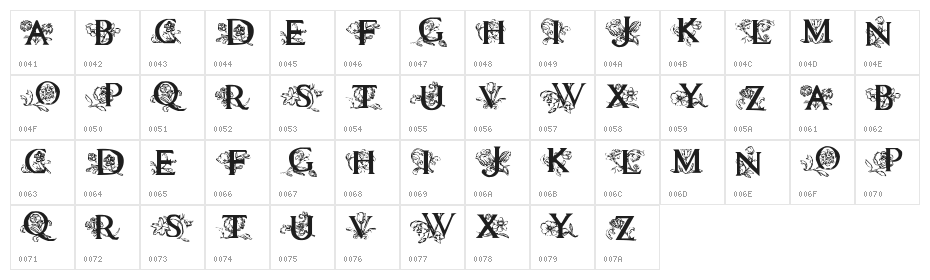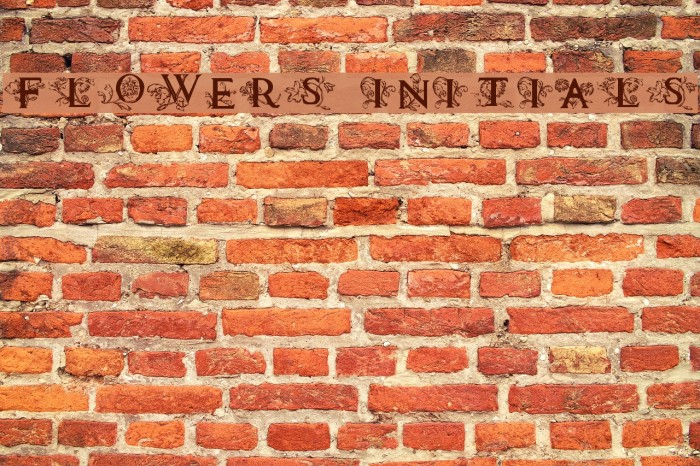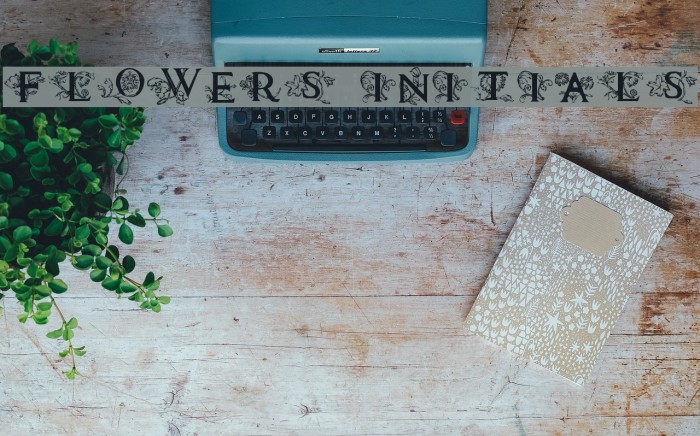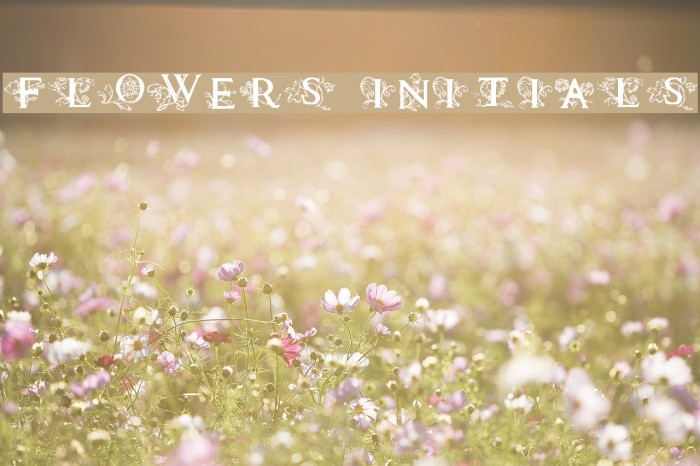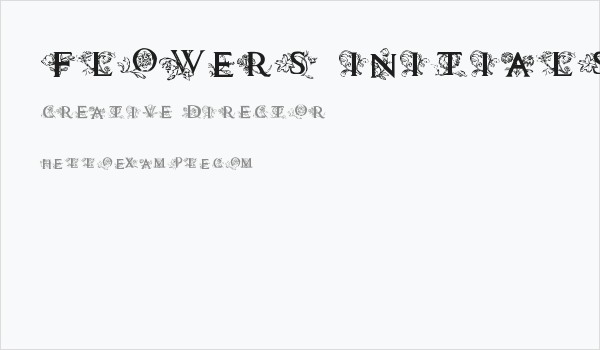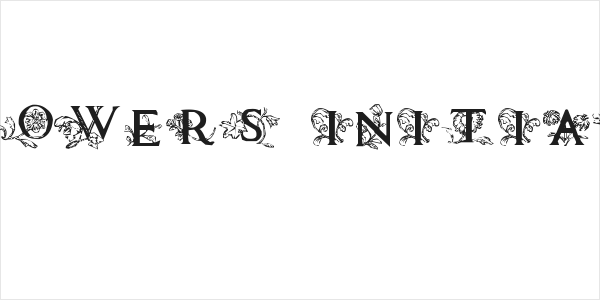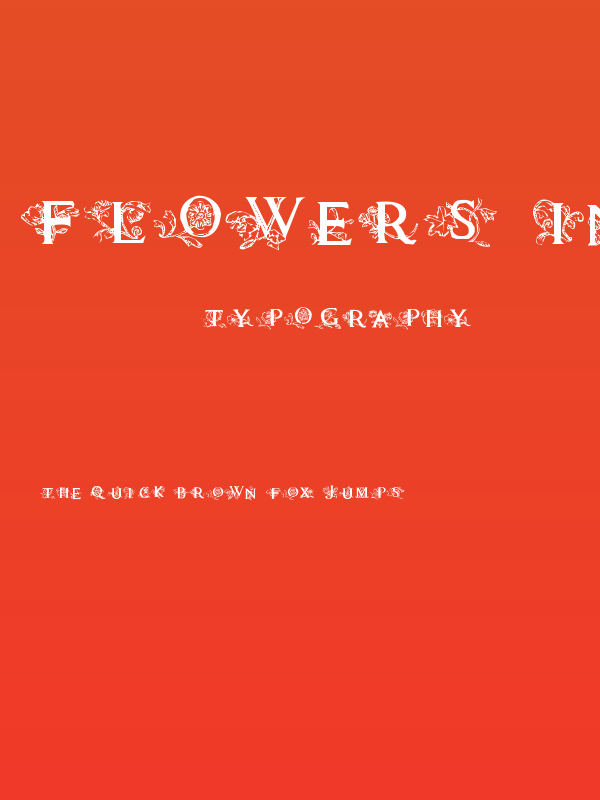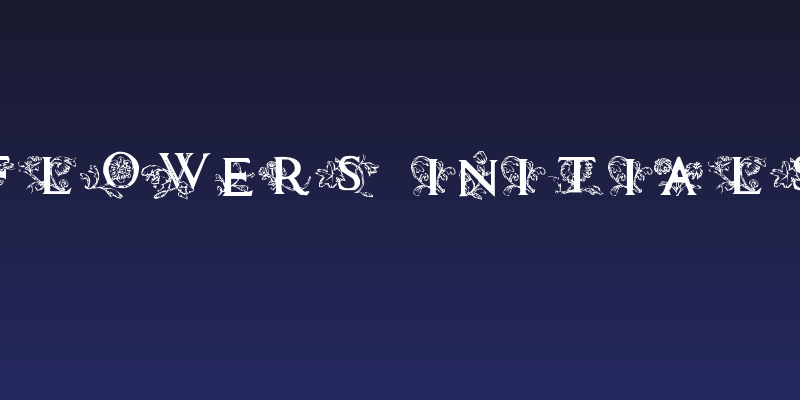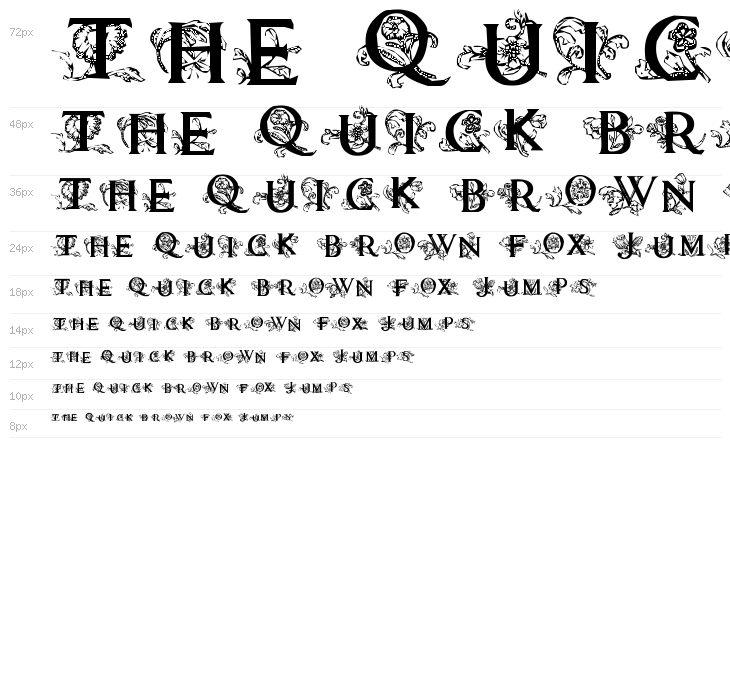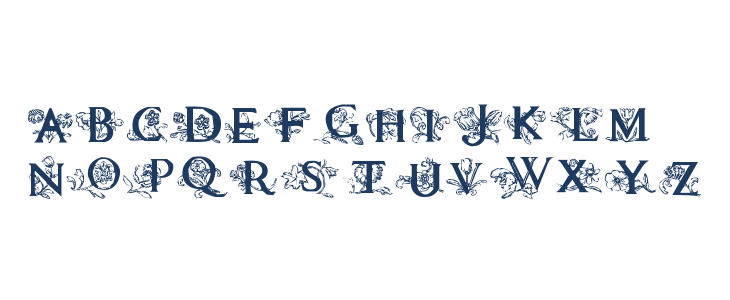
Flowers Initials Font
| Caso d'uso | Headlines, Decorative text |
| Progetti proposti | Ideal for wedding invitations, greeting cards, branding for luxury products, and decorative headings. |